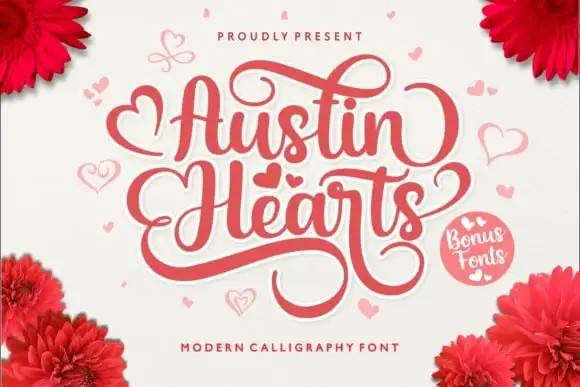
Austin Hearts Script Font
A Austin Hearts Script Font é uma elegante fonte tipográfica que traz uma base variável, linhas suaves, estilo moderno e profundidade do amor. Composta pelo designer Holydie Studio em seu espaço de criação 99designs, esta fonte é um verdadeiro toque de luxo para qualquer projeto gráfico que busque romance e sofisticação. As letras são incrivelmente estilizadas com swashes extravagantes, criando uma sensação de atração irresistível. Ideal para personalizar anúncios de casamento, cartões de felicitações ou até mesmo marcas pessoais que expressam seu amor de forma única e profunda. Uma fonte que não só deixará sua marca sobre qualquer projeto onde for usada, mas também fará seus clientes caírem em amor ao romantismo do design.